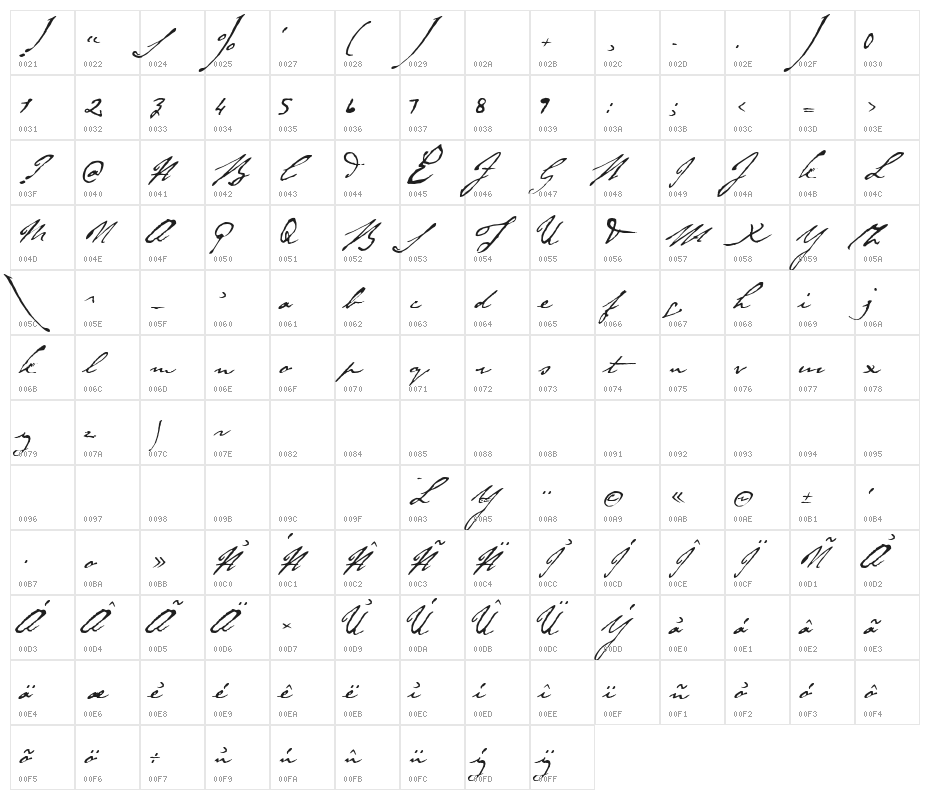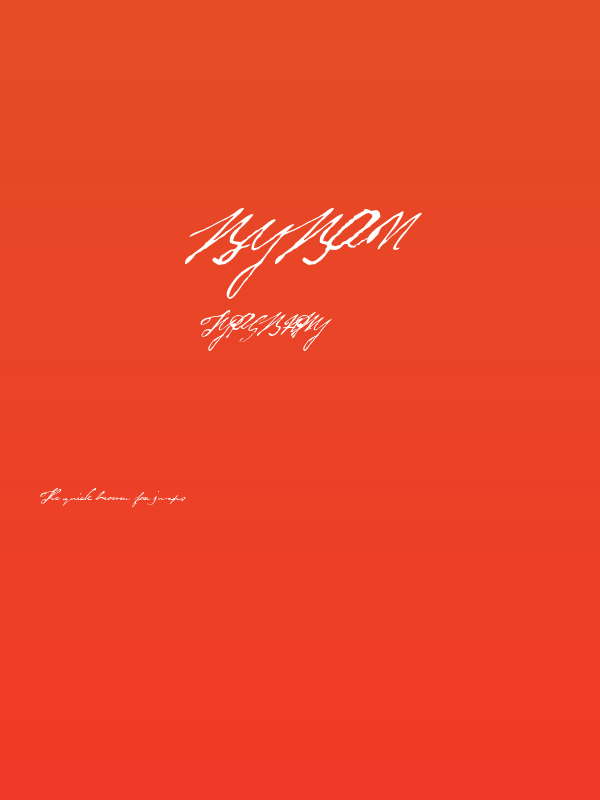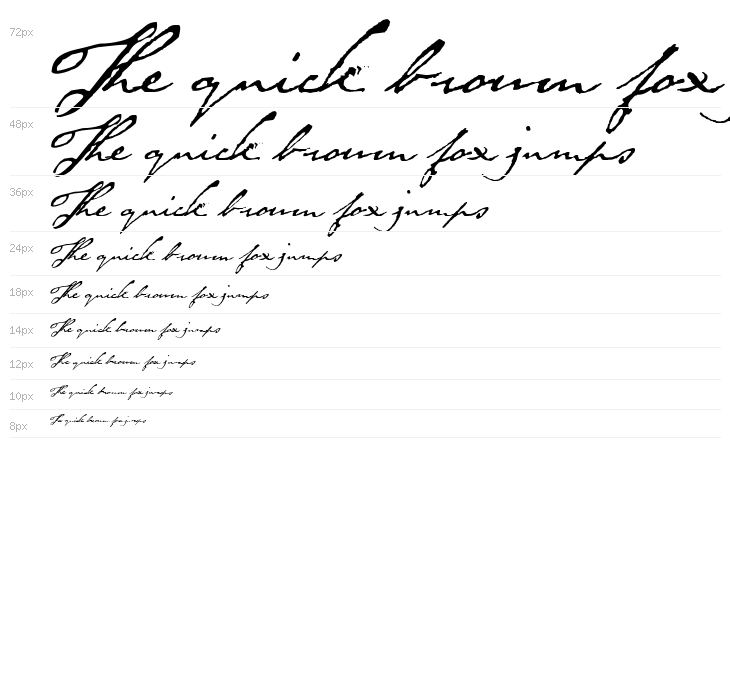
Byron Font
✎ Calligraphic
| Kategorien | Calligraphic |
| Anwendungsfall | Logos, Invitations, Personal Correspondence |
| Vorgeschlagene Projekte | Ideal for wedding invitations, personal letters, branding for artistic products, and any project that benefits from a personal, human touch. |